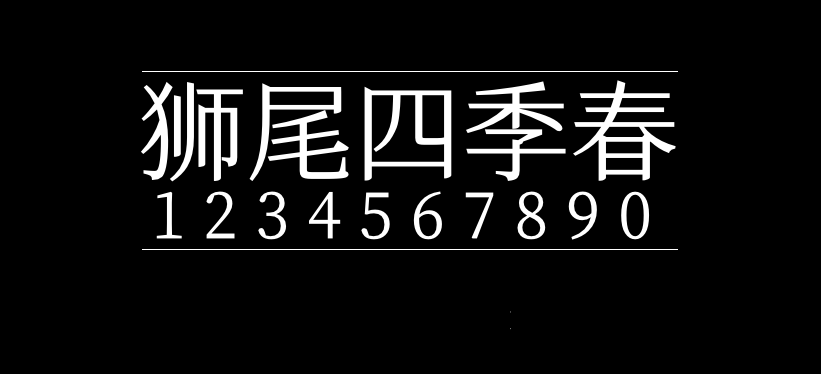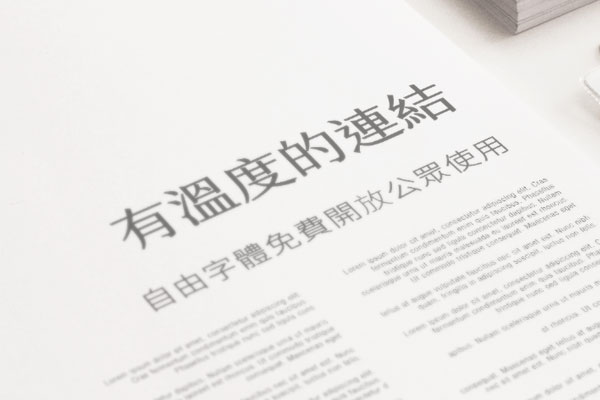
狮尾四季春
狮尾四季春(Swei Spring)是Max偶然看到新闻中图片横幅中的字体,可能是金萱的字体,非常特别,这款字体把黑体和宋体结合了在一起,看上去非常好看。受到启发,于是Max通过程序修改思源宋体,把思源宋体里的右边三角形衬线拿掉,并帮字体取名为狮尾四季春。虽然不太完美,但是看上去感觉还不错。
狮尾四季春是基于思源宋体改造,看上去会更加简明现代化,版面效果清新轻快。缺点是比较轻,横笔明显极细。和思源宋体一样,狮尾四季春支持简体中文、繁体中文、韩文与日文,并且支持6个字重。